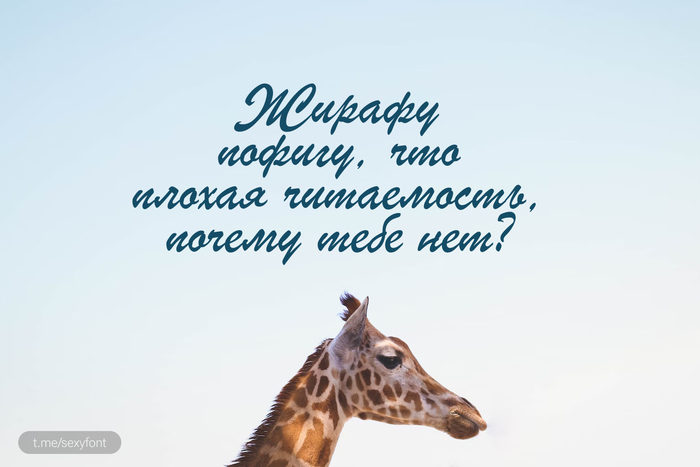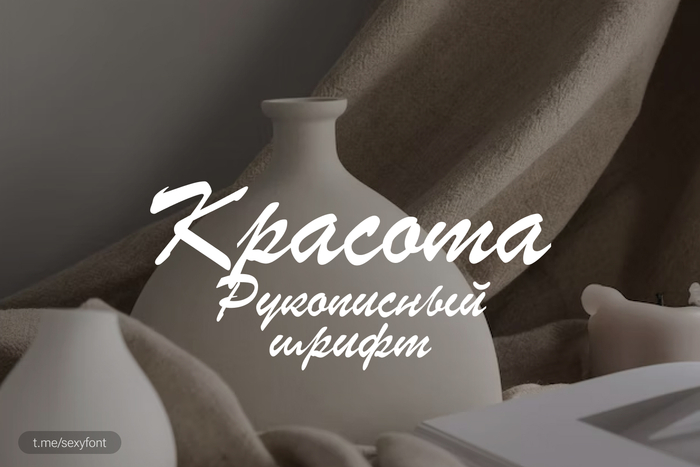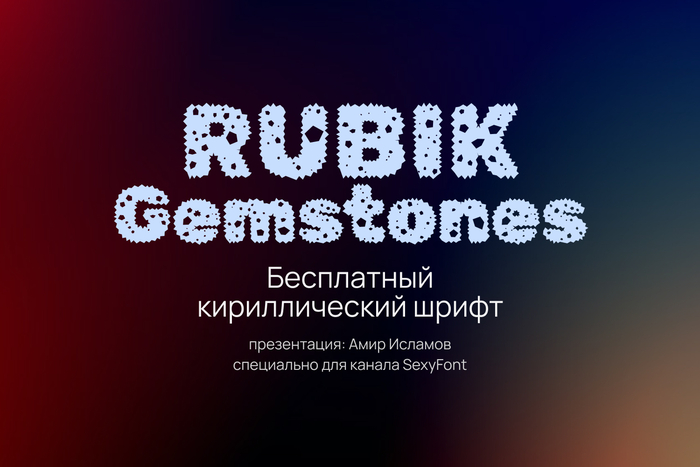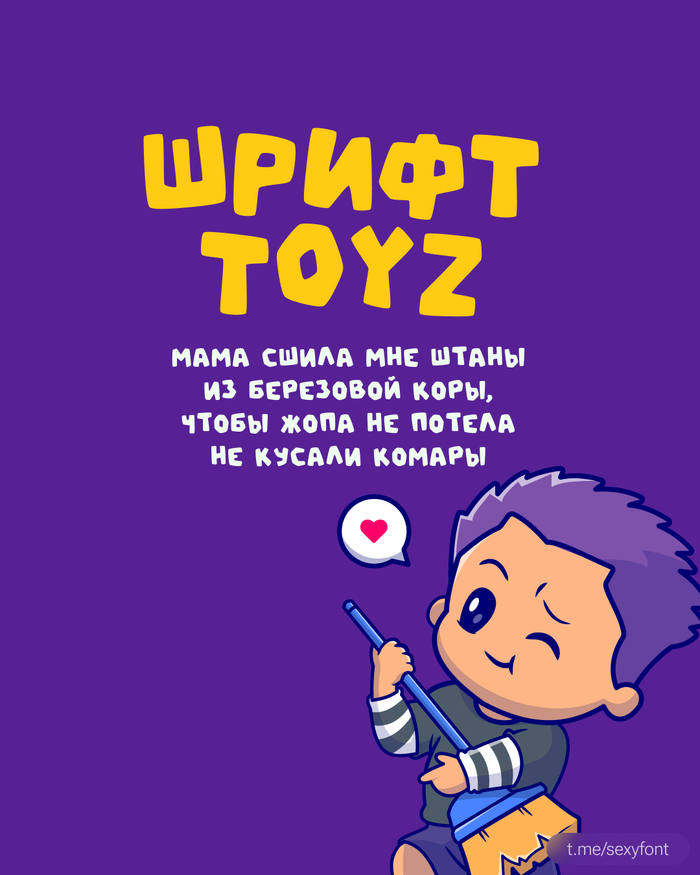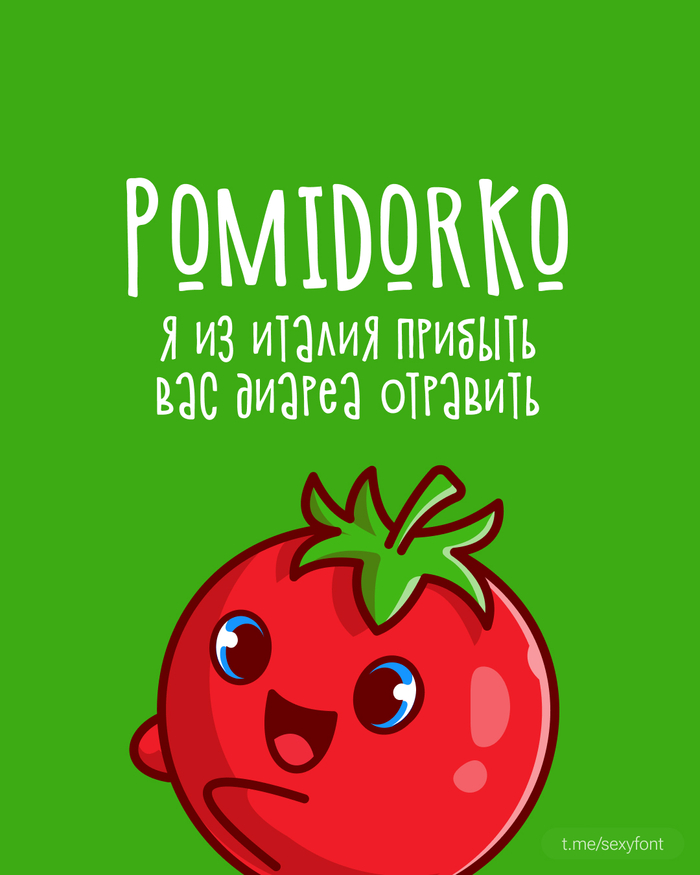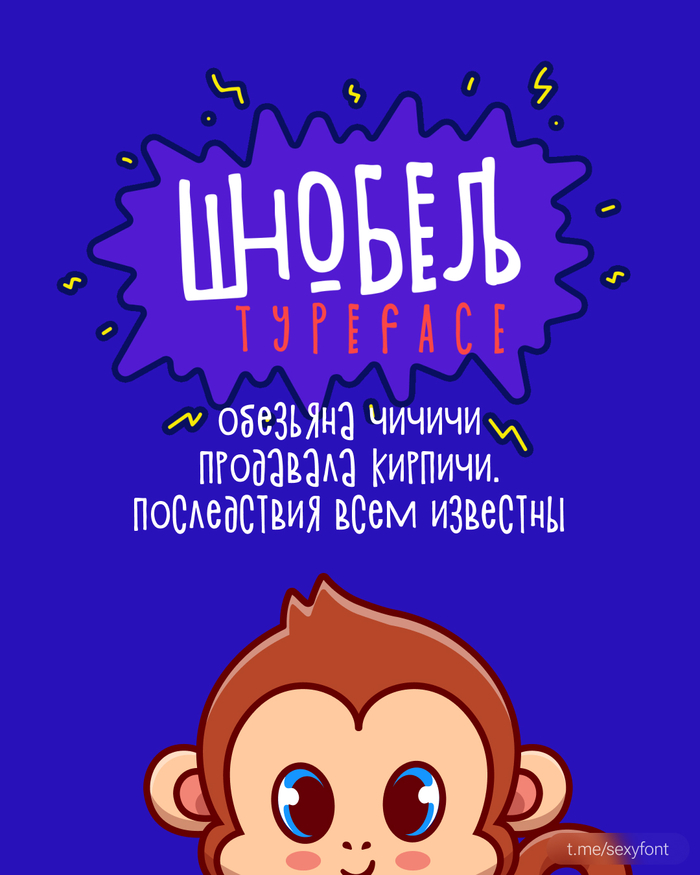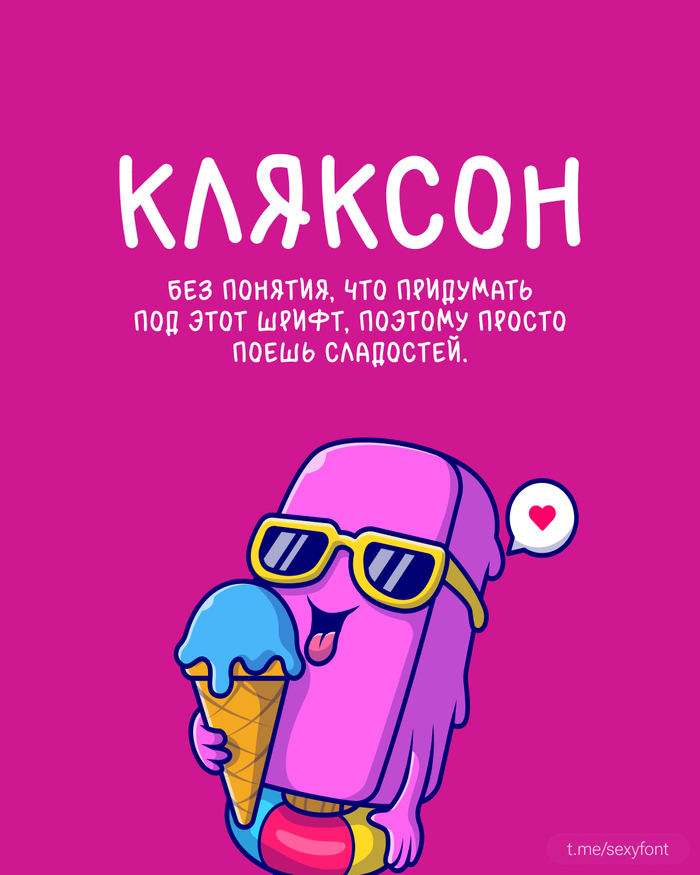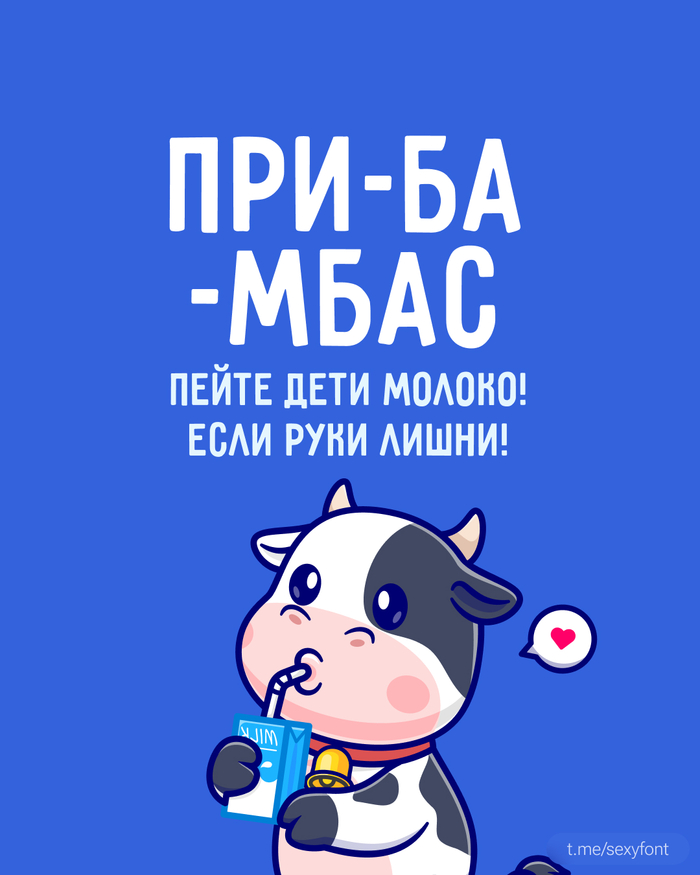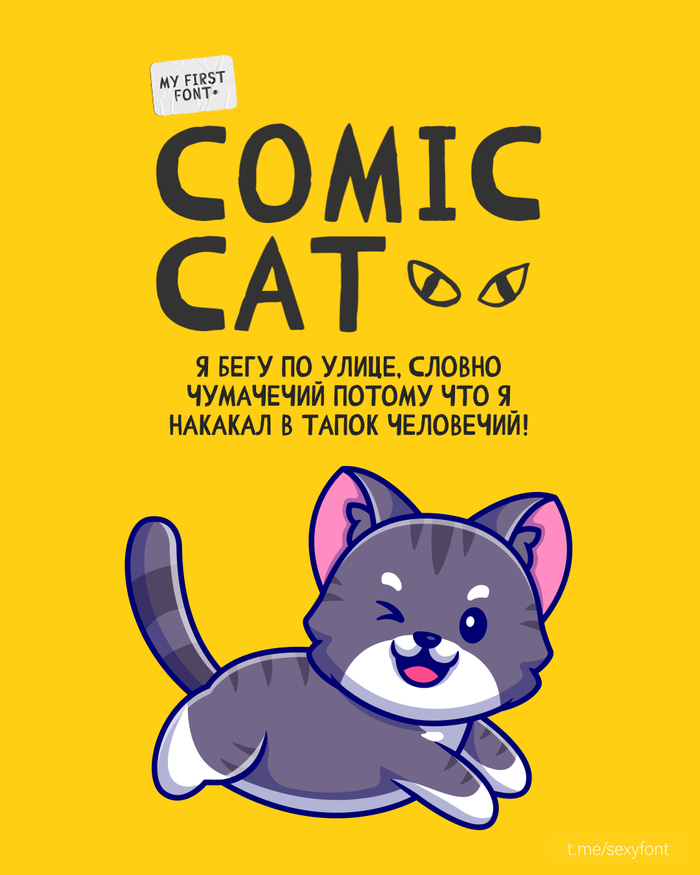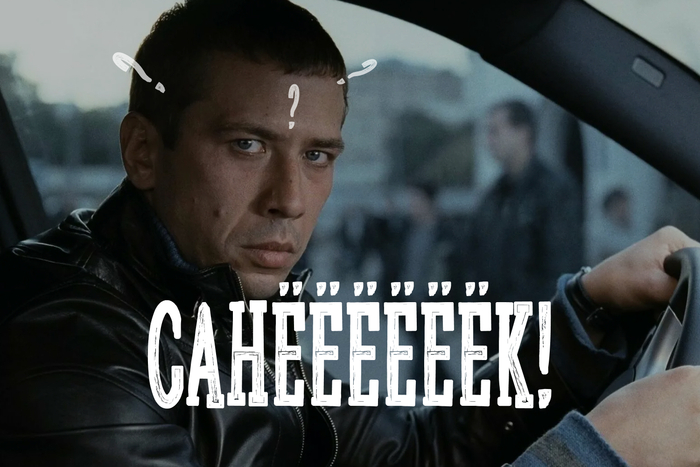
Шрифт Чеховский. Антиква
Давно у нас не было годной антиквы. Разрешите представить. Шрифт – Чеховской. Я не нашел у автора ни бехансика ни личного сайта. Просто откопал на просторах инета. А шрифтец то вполне годный. Презентацию естественно пилил тож сам. Чтобы тебе было удобно рассмотреть его. Понять, где пригодится.
От автора: "Назван в честь Юрия Борисовича Чеховско́го, на излёте нулевых годов текущего столетья, — перевозчика декораций на киностудии «Ленфильм»"
Бесплатный рукописный шрифт
Ляпота. Красота. Милота. Очень красивый открыточный рукописный шрифт. Отлично подойдет для открыток и приглашений. Главное не писать им большие абзацы. Иначе читаемость срежется нахрееен и все. Абздец. Аккуратно в крупных заголовках и нормалек)
Колючий шрифт Rubik-Gemstones
«10 лет изучаю ушу. Ща за жопу тебя укушу». – Девиз этого шрифта. Страшно-веселый. Чем-то похож на микроба и зверька волосатого. Называется «Rubik-Gemstones» но мне хочется называть его «Биба»
7 бесплатных кириллических шрифтов. Идеальных для детских тематик
Привет! Сегодня этому сообществу – неделя. Не ожидал, что на пикабу это зайдет) Подготовил для вас новую презентацию. Веселые шрифты для детских тем. Где-нибудь да точно пригодится. Заголовок у всех делал капсом, остальные наборным. (для наглядности)
Шрифт "Санёк"
Саня ты в порядке? Ты в порядке? Саня!!! Васек уже был. Настал час Сани. Кириллизация шрифта от Iordanis Passas. Веселый шрифт. Отлично подойдет под юмористический дизайн, под кофейню и под какой-нибудь барбер.
Kurochka Lapkoi
Куд-кудахнуться можно. Веселый кириллический шрифт.
Отлично подойдет для имитации корявого почерка. Возможно копия твоего. Давно у нас не было веселых каракульных шрифтов. Получите! Распишитесь!
Шрифт Belarus
Беларусь. Или Белоруссия. Не будем спорить где верно. Все, итак, знают как.
Хотя как без споров на пикабу?) ГО!
Красивая ленточная антиква. Использовать лучше в заголовках. В длинных абзацах она теряется, это мы видимо в стишке про воробушка. Хорошего урожая во всем!
Шрифт quinquefive
Дизайнеры денди или тетриса ссались бы кипяточком от этого шрифта) Прикольный пиксельный и полностью бесплатный quinquefive. Квинкифайф? КвинкиКайф!
Да будет так. Пользуйся!)